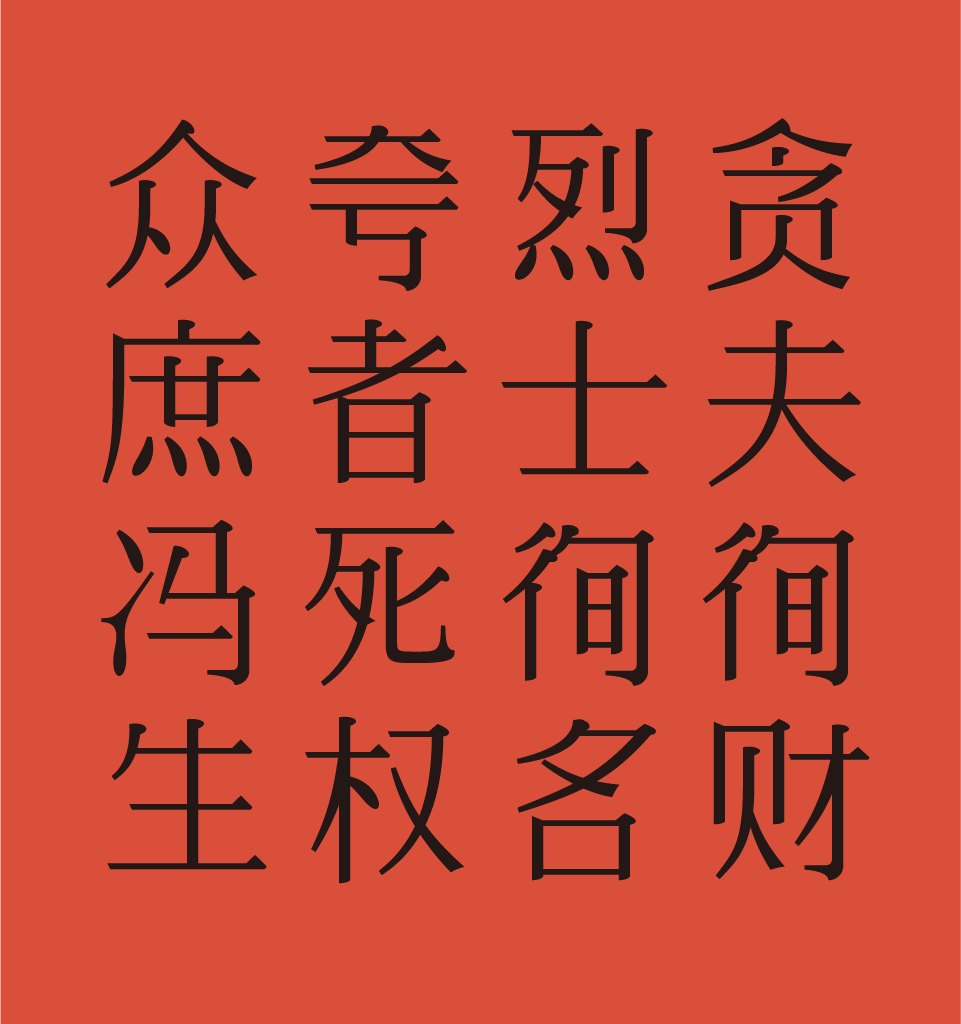
余繁丹青宋字体信息
余繁丹青宋
字体风格: 宋体
这是一款实验字体,旨在演示完全程序生成的字体可以做到哪种程度,所以一些效果不佳之处并没有选择后期手工修正。目前看来还是过于粗糙,完全无法与手工精心制作的字体相提并论,只能算是未来可期吧。
汉字骨架由动态组字系统繁星生成,源数据 yufandanqing.fas.json
西文以及标点取自思源宋体。